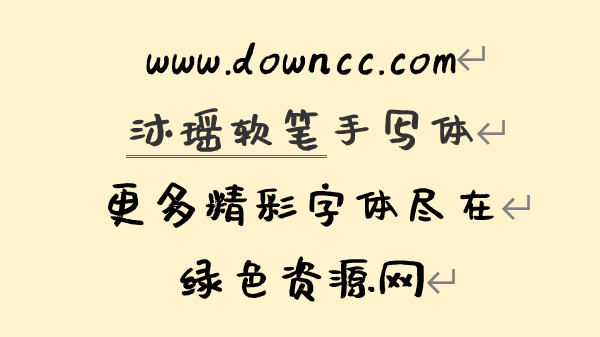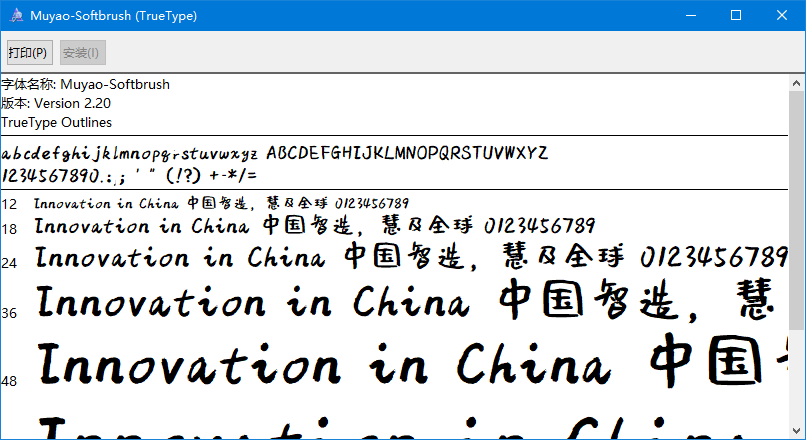
沐瑤軟筆手寫體字體為你提供了一種非??蓯鄣淖煮w,該字體采用了萌萌的風格,讓你會覺得這款字體非常的可愛。字體適用范圍非常廣,只要是支持ttf格式的地方都可以使用。歡迎下載!
我的成長經(jīng)歷中,沒有刻意練過手寫字。不過,在手寫海報方面倒是有一段經(jīng)歷。和現(xiàn)在的直接噴繪印刷不同,學生時代經(jīng)常需要手寫海報,經(jīng)常一式多份。原本是需要用馬克筆寫POP字,但是畢竟馬克筆對于我的學生時代來說,價格很昂貴,于是大家都用排筆+廣告色的方式進行創(chuàng)作。與傳統(tǒng)的中文書法楷隸行草不同,這種書寫方式可以把字寫得較為可愛,也算是一種更加手寫化的廣告字體。
1、采用卡通手寫風格,給你眼前一亮的感覺
2、字體稍微粗一些,對于小字的顯示可能不太好,不建議在手機上用